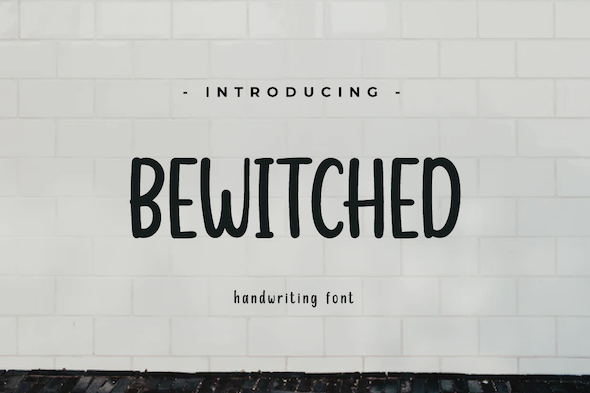
Download Font PPT Keren yang Menarik – Menyampaikan pesan atau materi kepada audiens merupakan tujuan utama presentasi. Seorang presenter (presentator) tentu perlu mempersiapkan berbagai hal untuk mempersiapkan penampilan yang maksimal.
Lanjut, masih mengenai menyiapkan ppt. Nah, satu komponen penting yang mempengaruhi tampilan ppt adalah jenis font yang Anda gunakan. Font untuk ppt yang Anda pilih tentu akan memberikan kesan yang besar kepada audiens.
"Font PPT yang Anda pilih mempengaruhi kesan yang didapatkan audiens."
Pada kesempatan kali ini, kami akan bagikan font-font bagus yang menurut kami sangat pas Anda pilih untuk mempercantik slide presentasi (ppt) yang Anda buat. Tentunya Anda bisa men-download font untuk ppt yang kami sebutkan di sini gratis.
#1 – Config
#2 – Montserrat
#3 – Bebas Neue
#4 – Lato
#5 – Raleway
#6 – Lemon Milk – [Font PPT Keren untuk Heading/Judul]
#7 – Coolvetica
#8 – Harabara
#9 – Roboto Condensed – [Download Font PPT Bagus untuk General]
#10 – Front Page Neue – [Font untuk ppt yang menarik anak SD]
#11 – Roboto – [Font PPT yang Bagus untuk Teks]
#12 – Oswald [Font PPT Keren untuk Teks]
#13 – Maven Pro
#14 – Ubuntu
#15 – Alpaca
#16 – Cocogoose – [Font untuk PPT Heading/Judul]
#17 – Comfortaa
#18 – Geo Sans Light – [Font bagus PPT untuk Teks dan Judul]
#19 – Mont – [Font PPT Keren untuk Teks dan Judul]
#20 – Code – [Font untuk PPT Keren Heading/Judul]
#21 – Modern Sans Light
#22 – Overgrow
#23 – Poetsen One – [Font untuk ppt yang menarik anak SD]
#24 – Louis George Café – [Font PPT yang Bagus untuk Konten Teks]
#25 – Heading [Font yang bagus untuk Judul PPT]
#26 – Download Font untuk PPT: The Next Font
#27 – Download Font PPT: Sansation
#28 – Font PPT: Metropolis
#29 – Font PPT: Dosis Extra Light
#30 – Font PPT: Amatic SC
#31 – Font PPT: Im Fell French Canon
#32 – Font PPT: Dense
#33 – Font PPT: Steelfish
#34 – Font PPT: Libre Baskerville
#35 – Font PPT: Cornetta
#36 – Font PPT: Bewitch
Cara Memilih Font yang Baik untuk PPT
Jika Anda ingin memilih font sendiri menggunakan berbagai situs di atas atau mengkombinasikan font tersebut, ada baiknya untuk memperhatikan bagaimana cara memilih font yang tepat untuk PPT. Berikut cara mengkombinasikan dan memilih font tersebut:
- Jangan menggunakan tulisan tegak bersambung dan rumit karena akan sulit dibaca.
- Jangan banyak menggunakan huruf besar (kapital) dalam isi materi. Hal ini karena akan membuat tulisan sulit dibaca dan akan membuat tampilan PPT terlihat penuh. Sebaiknya gunakan font kapital untuk judul atau singkatan.
- Jangan terlalu banyak menggunakan kombinasi font karena hal itu akan membuat tampilan PPT tidak formal, profesional, dan konsisten.
Tentu, font yang bagus untuk ppt tidak se’ramai’ dan unik font untuk stiker, font logo, maupun font handwriting. Font untuk ppt relatif lebih simple, tegas, dan formal.
Hal tersebut akan menunjang penguatan pesan pada presentasi yang Anda lakukan.